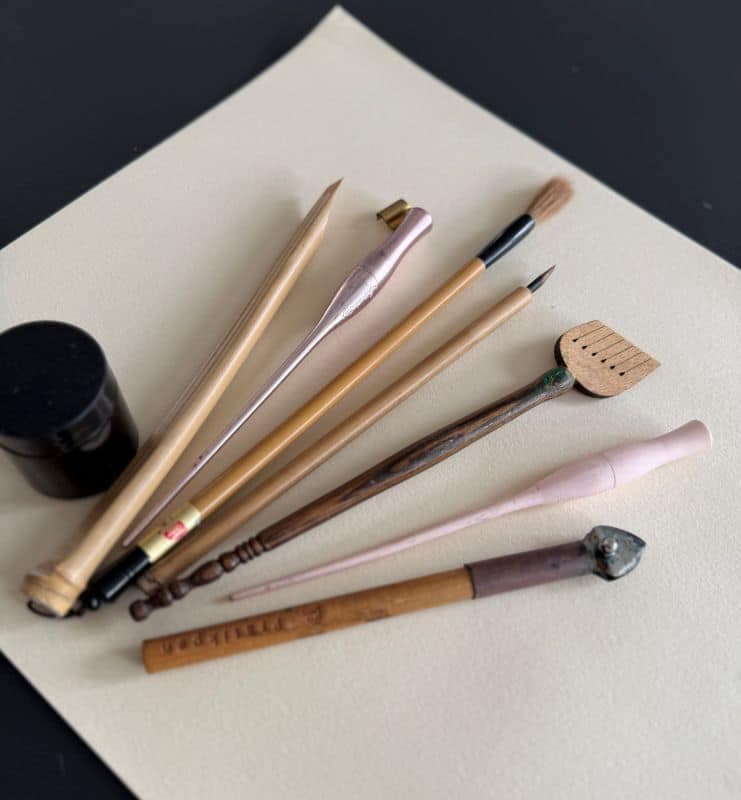
הקליגרפיה היא לא רק אמנות עתיקה — היא גם דרך להכניס יופי, דיוק ואמירה אישית לכל מילה. בשנים האחרונות גוברת ההתעניינות בתחום האמנות הזה.
אם גם אתם רוצים להתחיל לעצב תוצרים עם טקסטים הכתובים בצורה יפהפייה ומוקפדת – המאמר הזה נכתב במיוחד בשבילכם.
במדריך זה נסקור את כל מה שאתם צריכים לדעת כמתחילים כדי להרכיב לעצמכם סט כלים לקליגרפיה שיאפשר לכם להתחיל נכון ולפעול נכון – בלי לבזבז זמן, כסף או השראה, ובלי לצבור כאבי לב מטעויות בדרך אל הידע הנכון והביצוע המושלם.
לפני שרצים לקנות עטים וניירות, חשוב להבין שקליגרפיה טובה מתחילה בהיכרות עמוקה עם הכלים. לא כל עט מתאים לכל סגנון, ולא כל נייר מחמיא לכתיבה קליגרפית.
כשבוחרים כלים לקליגרפיה, חשוב לשים לב לנוחות העבודה, ליכולת לשלוט בקווים ולתגובות של הדיו על המשטח.
גם לעובי הקו, לזווית הכתיבה ולגמישות הכלי יש השפעה עצומה על התוצאה. התחלה נכונה כוללת בחירה מודעת, שמותאמת לא רק למראה הרצוי – אלא גם לחוויית הכתיבה עצמה.
יש מגוון רחב וטוב של כלים לקליגרפיה, וכל אחד מהם משפיע על הסגנון, התחושה והתוצאה הסופית. בין אם אתם נמשכים לכתיבה חופשית או לצורות מדויקות – בחירת הכלים הנכונים תאפשר לכם לבטא את עצמכם בצורה חלקה ונעימה. הנה סקירה של הכלים המרכזיים שכל מתחיל צריך להכיר.
הבסיס לכל יצירה. עטים עם ראש גמיש (מברשת) מתאימים לכתיבה חופשית וזורמת, ועטים עם ראש שטוח מתאימים ליצירת אותיות גיאומטריות ומדויקות. מתחילים רבים בוחרים להתחיל בעט מברשת – הוא מאפשר תנועה טבעית של היד.
לא כל נייר נולד שווה. נייר טוב לקליגרפיה הוא כזה שלא סופג דיו יתר על המידה ולא “מדמם”. עדיף להתחיל עם נייר חלק, באיכות גבוהה, שמתאים לדיו או לעטים מברשתיים.
אם אתם עובדים עם עט טבילה – השקיעו בדיו איכותי. דיו זול יכול לפגום באחידות הקווים ולפגוע בחוויית הכתיבה.
לפני כל יצירה, כדאי לשרטט שורות מנחות. זה אולי נשמע טריוויאלי, אבל גם אמנים מנוסים מתחילים עם קווים מנחים שיעזרו לשמור על מבנה נכון.
אין תחליף לתרגול עקבי. רכשו חוברות הדרכה או השתמשו במדריכים דיגיטליים.
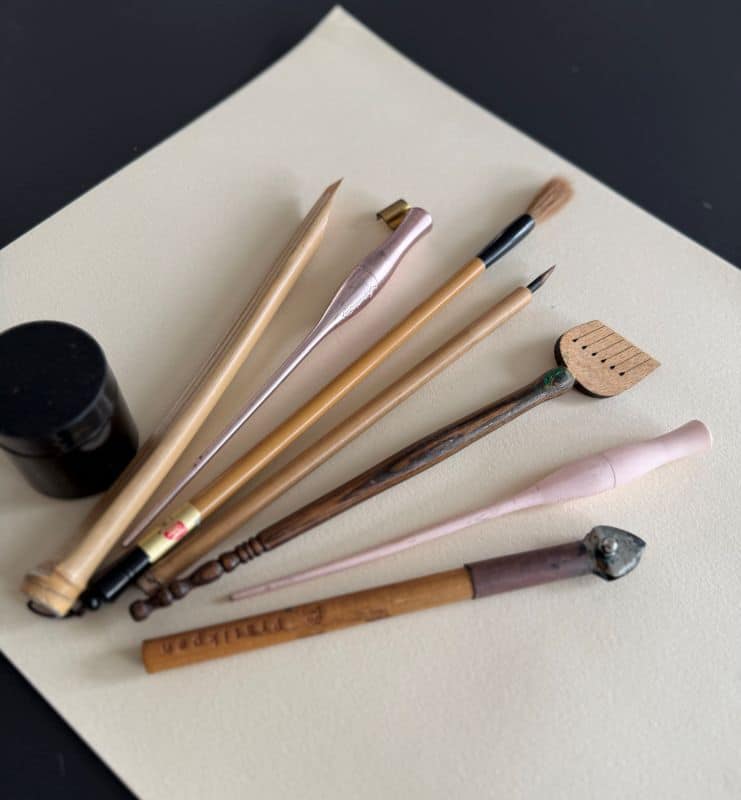
כלים לקליגרפיה הם רק ההתחלה. כשאתם עובדים, אל תשכחו לחשוב על ההקשר התרבותי והעיצובי של מה שאתם יוצרים.
טיפוגרפיה יהודית, למשל, נושאת בתוכה מסורת עשירה של כתיבה מהודרת, מכתיבת סת”ם ועד עיצוב ספרים עבריים לאורך הדורות.
מעצבים רבים משלבים קליגרפיה בעבודות דיגיטליות, ולעיתים אף סורקים אותיות שכתבו ביד כדי ליצור פונטים דיגיטליים מקוריים.
שימוש נכון של כלים לקליגרפיה, גם כשמדובר בעיצוב דיגיטלי, מאפשר להביא לידי ביטוי את הדיוק והייחוד של הכתיבה הידנית.
בעולמות של קליגרפיה סינית, כמו בעולמות של קליגרפיה עברית, הכול מתחיל מהיסודות – מברשות מיוחדות, דיו סיני, נייר אורז וכללי עבודה מסורתיים שעוברים מדור לדור.
מדובר באמנות עתיקת יומין, בעלת שפה חזותית עשירה, שבה לכל תנועה של המברשת יש משמעות. זו שפה שיש בה קודים ברורים, היררכיה צורנית ומשקל רגשי עצום.
אך בסופו של דבר, כמו בכל קליגרפיה איכותית – המשמעת, הדיוק והחזרתיות הם הלב הפועם של היצירה, והם אלו שמובילים לשליטה מוחלטת בצורת האות ולביטוי אישי עמוק דרך הקו.
לסיכום: לא חייבים הרבה כדי להתחיל – רק מדויק. אל תמהרו לקנות את הסט הכי יוקרתי. התחילו מסט בסיסי, איכותי, שיעזור לכם להבין מה הסגנון שמתאים לכם.
זכרו: כלים לקליגרפיה טובים הם כאלה שמרגישים לכם נוח ביד, ושעוזרים לכם לייצר קווים מדויקים. התחילו לאט, תתרגלו, תשפרו – ובעיקר, תהנו מהדרך.
הכלים לקליגרפיה עט קליגרפיה, נייר איכותי, דיו, סרגל ועפרון – אלו יספיקו לכם להתחלה מעולה. בהמשך תוכלו להרחיב את הסט.
הקליגרפיה של השפה עברית מבוססת על כתב סת”ם וכתיבה ייחודית לאותיות עבריות, בעוד הקליגרפיה של המזרח, ובעיקר סין, כוללת תנועות מברשת ומסורת סמלית ייחודית לתרבות הסינית.
ניתן להשתמש כהשראה פונטים בעברית, לשלב קליגרפיה ביד עם טקסט מודפס, או אפילו ליצור פונט דיגיטלי אישי מתוך כתב ידכם.
ניתן להתחיל לבד עם מדריכים וסרטונים, אך למי שמעוניין להעמיק – מומלץ להצטרף לסדנה מקצועית.